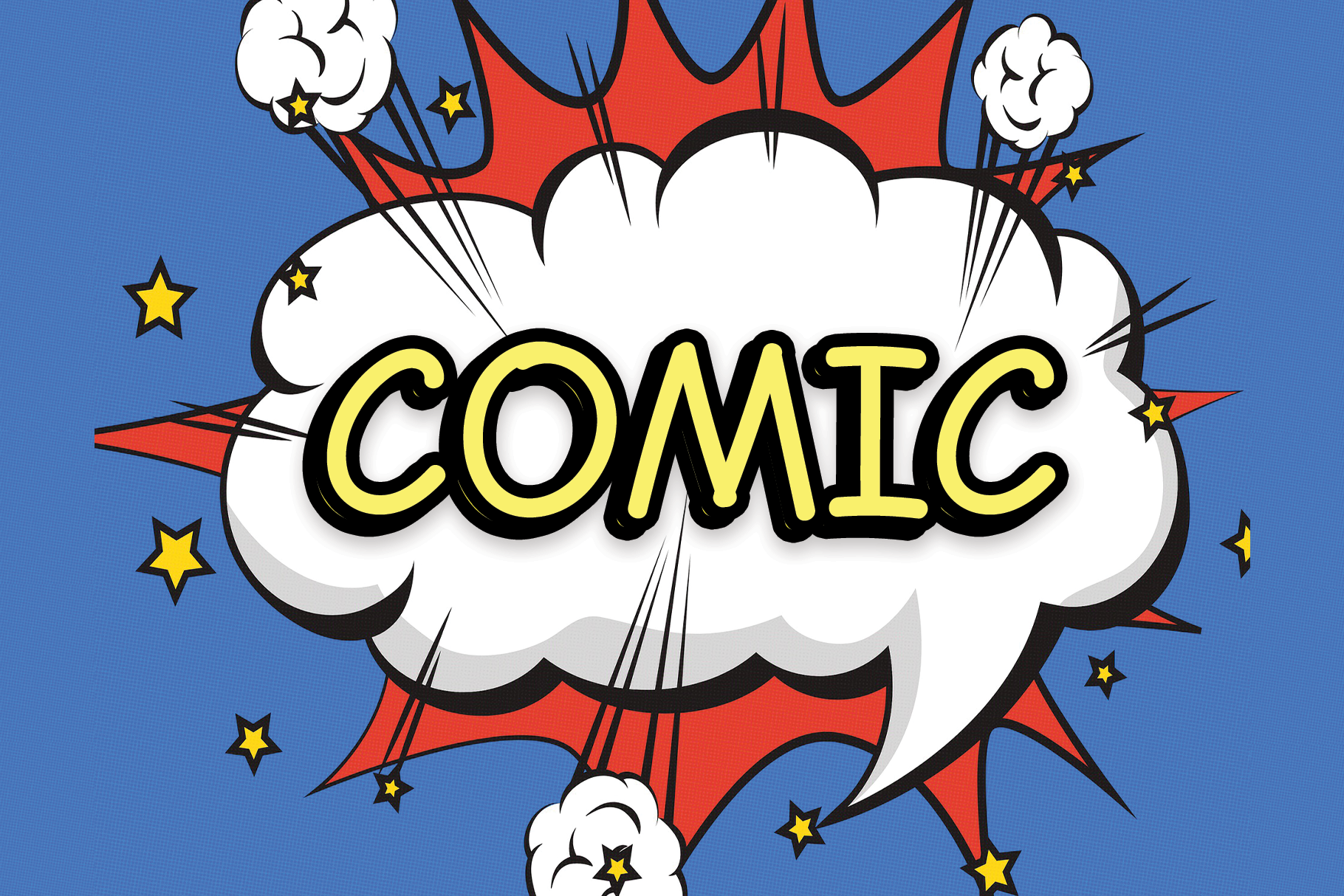
Esta é uma fonte de display desenhada com beleza e simplicidade. Ela se destaca tanto para aplicações relacionadas a personagens cômicas em designs, jogos infantis ou materiais educativos voltados para crianças, quanto para citações, títulos, nomes de marcas, capas de livros, cartazes e qualquer projeto que busque um toque de elegância. Seja ela para ilustrar uma publicação de criança em papel, criar letras exuberantes para o seu site ou personalizar a identidade visual de sua marca, esta fonte é uma escolha ótima. Ela oferece tanto versatilidade quanto beleza, tornando-a perfeita para vários tipos de criações visuais que desejam um toque divertido e moderno. É uma excelente opção para quem busca adicionar personalidade ao seu design.